Dalam dunia presentasi, PowerPoint telah menjadi salah satu media yang paling populer untuk membuat dan menyampaikan materi. Namun, sering kali kita terjebak dalam penggunaan font default PowerPoint yang membosankan. Padahal, font yang digunakan dapat mempengaruhi tingkat pemahaman dan minat audiens terhadap materi yang disampaikan.
Untungnya, ada banyak font PowerPoint keren yang tersedia secara gratis yang bisa Anda gunakan untuk meningkatkan desain presentasi Anda. Dalam artikel ini, kami menyediakan 45 font PowerPoint keren yang bisa Anda unduh dan gunakan secara gratis. Dari font yang simple hingga yang lebih aesthetic, kami telah merangkum beragam opsi untuk memenuhi kebutuhan desain presentasi Anda. Yuk, simak daftarnya di bawah ini!
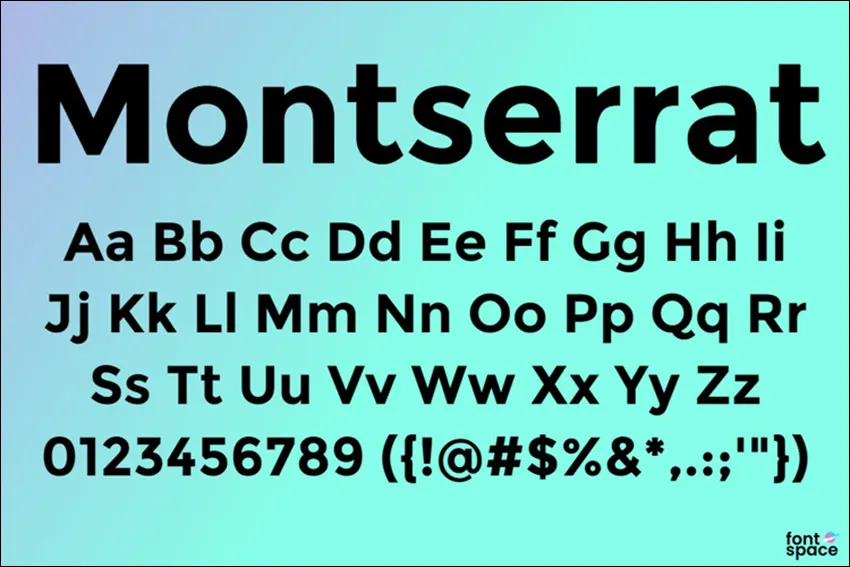
Font pertama adalah Montserrat, font sans-serif modern dengan desain tebal, profesional sekaligus menarik secara visual. Cocok digunakan untuk judul dan sub-judul PPT Anda.
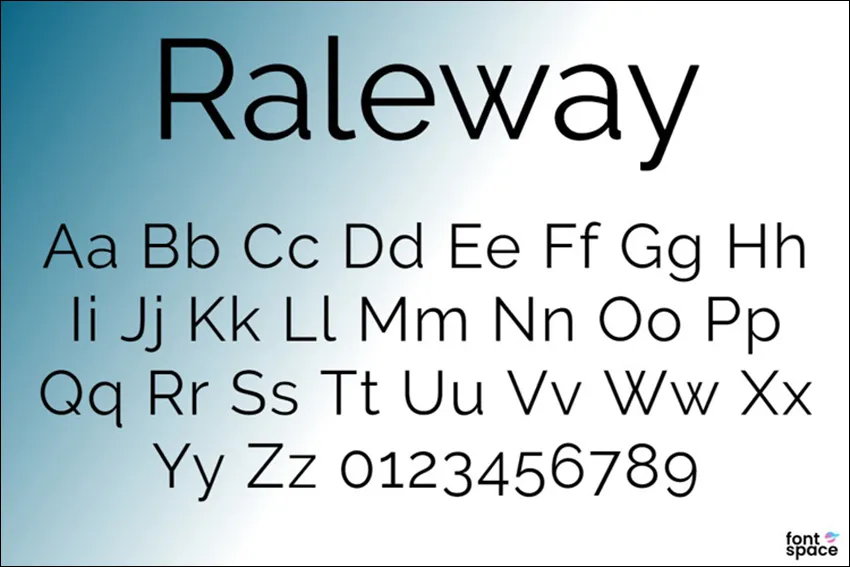
Font kedua adalah Raleway, font sans-serif dengan tampilan yang lebih ringan namun tetap artistik. Cocok digunakan pada hampir seluruh bagian powerpoint, baik judul, sub-judul, maupun body.
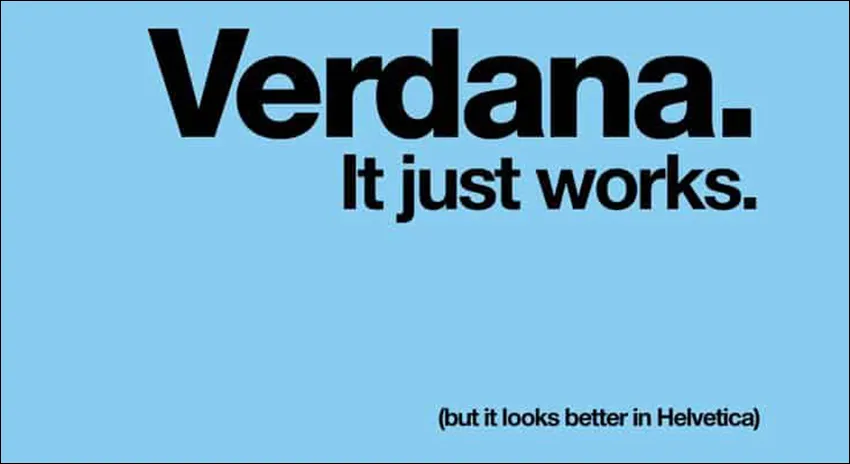
Selanjutnya adalah font Verdana, jenis font sans-serif dengan huruf kecil yang tinggi dan spasi yang lebar, sehingga membuat font ini mudah dibaca meski ukurannya kecil.
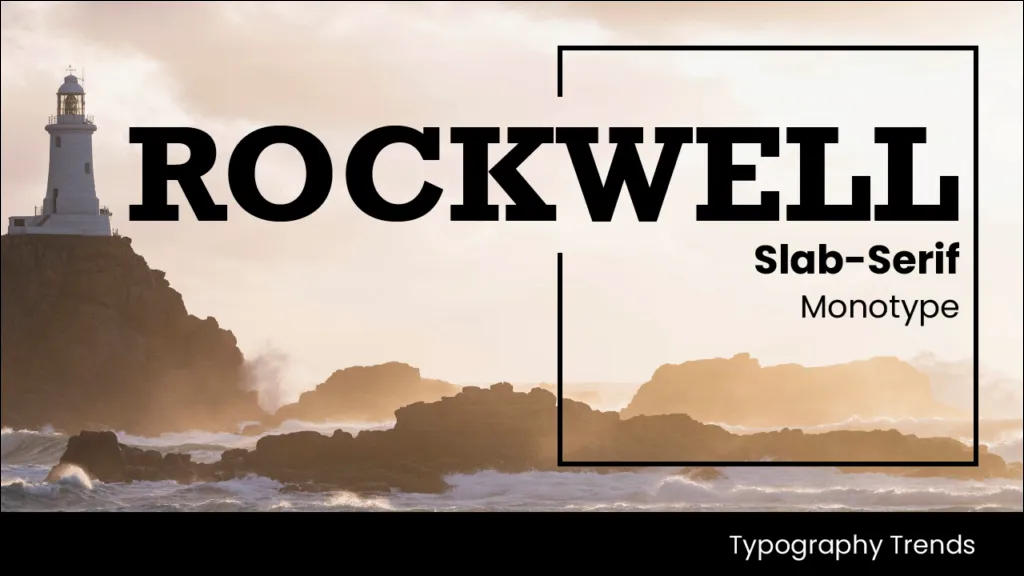
Font ini termasuk font slab-serif dengan desain yang kuat namun tetap hangat, cocok digunakan untuk bagian judul dan sub-judul PPT.
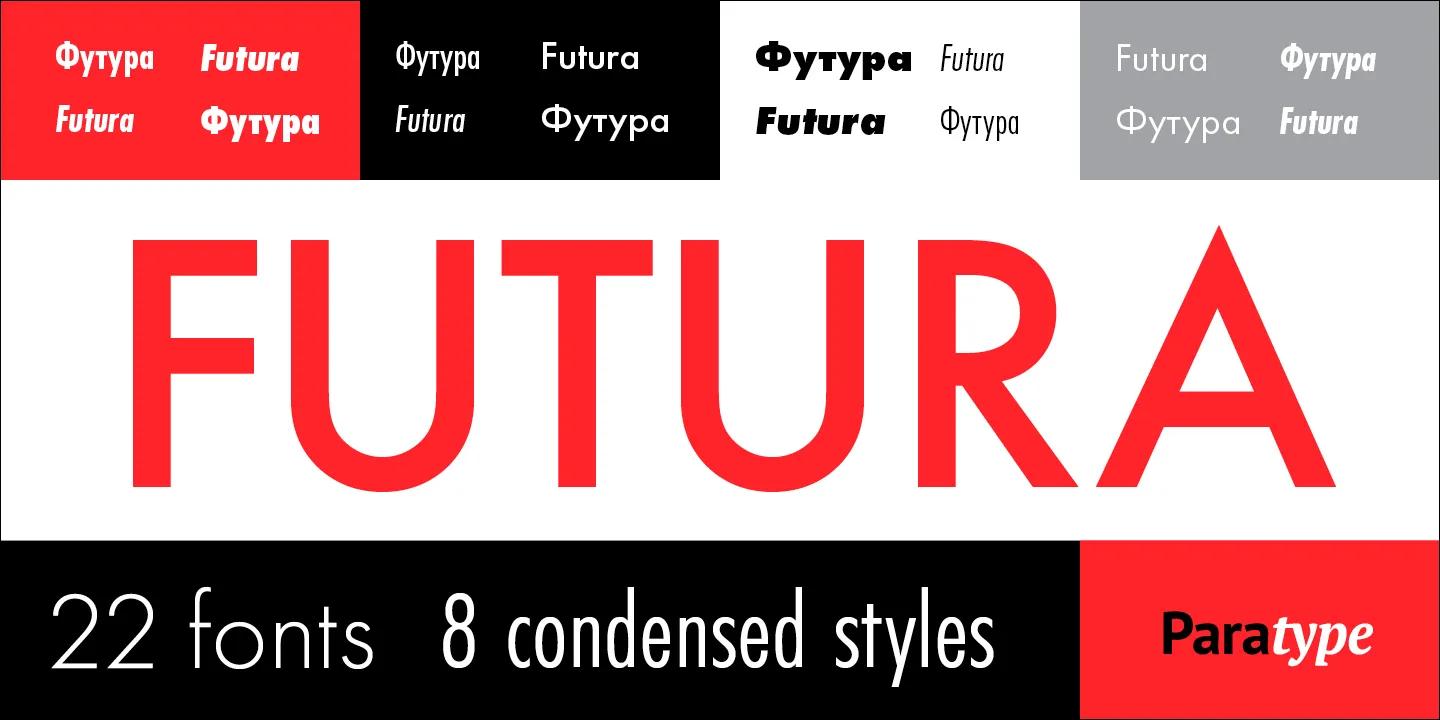
Font slab-serif ini memiliki desain yang bersih dan elegan, cocok digunakan pada seluruh bagian PPT, mulai dari judul hingga konten/body.
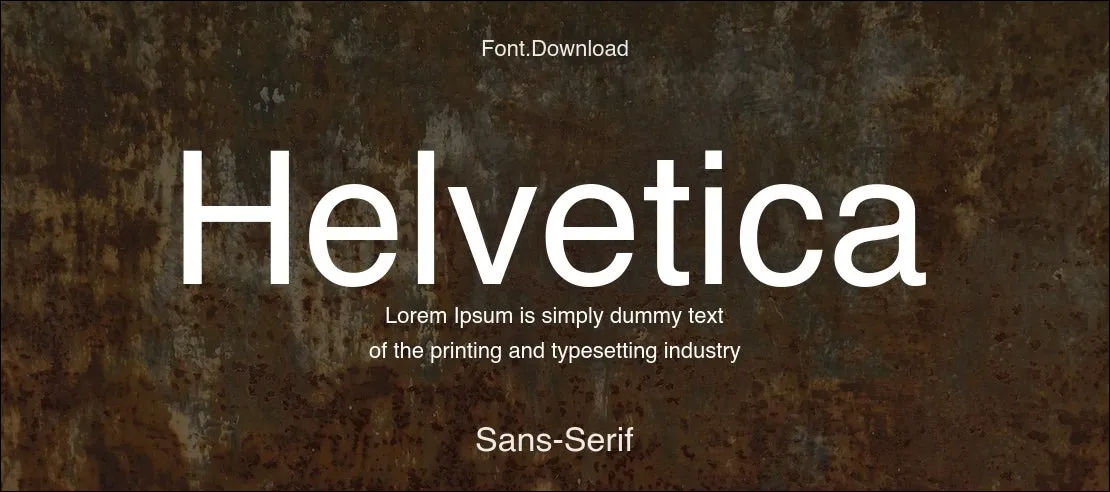
Helvetica merupakan font sans-serif dasar yang paling populer dengan bentuknya yang bagus dalam berbagai gaya, baik tebal maupun kapital semua, membuatnya cocok digunakan pada bagian judul atau sub-judul.
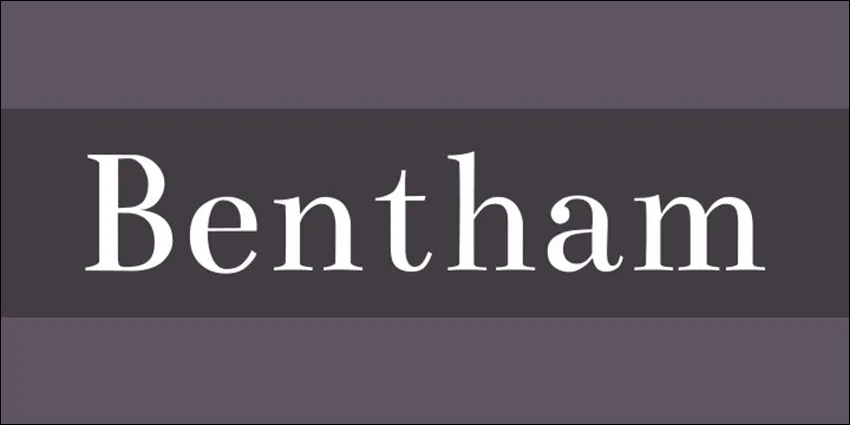
Bentham hadir dengan desainnya yang klasik dan spasi karakternya yang pas, membuatnya cocok digunakan pada bagian judul dan sub-judul PPT.
Font sans-serif ini menampilkan desain huruf yang kokoh dan kuat, membuatnya terlihat menarik jika digunakan pada bagian judul atau sub-judul.
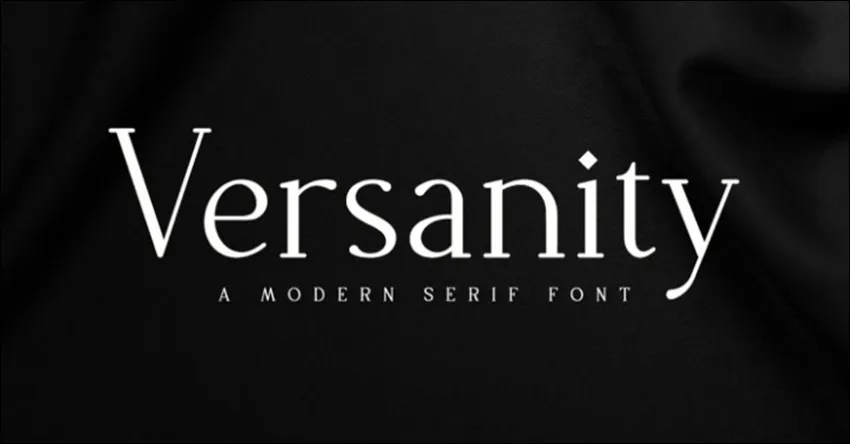
Versanity masuk ke dalam kategori font serif modern dengan desain yang halus dan elegan, cocok digunakan untuk bagian judul maupun sub-judul presentasi Anda.
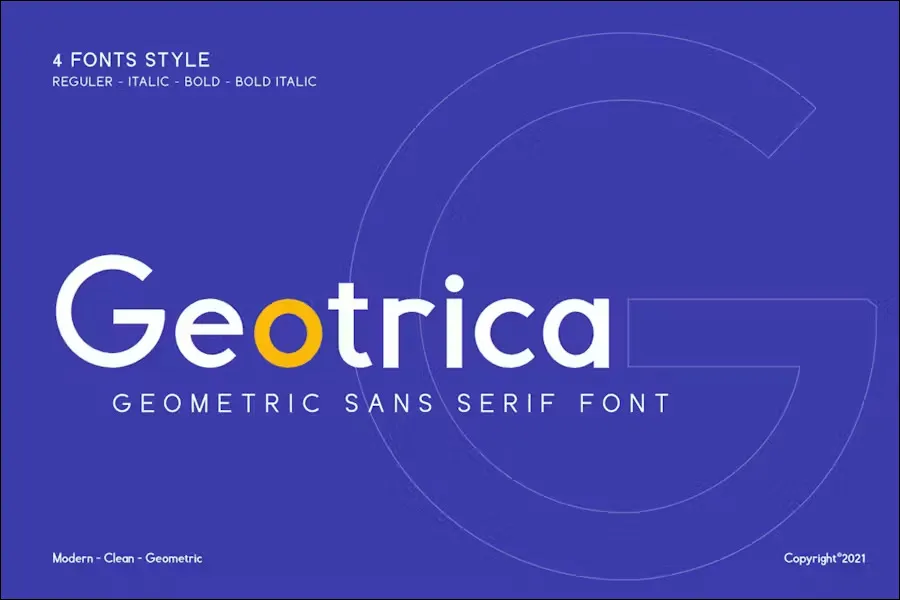
Sebagaimana namanya, font sans-serif ini memiliki bentuk geometris dan desain yang modern. Cocok digunakan untuk header atau sub-header PPT Anda.
Preface adalah font sans-serif dengan tampilan yang segar dan profesional. Cocok digunakan pada semua bagian PPT.
Font ini memiliki desain vintage yang mewah, cocok digunakan untuk bagian judul besar PPT.
Walton merupakan font sans-serif modern yang paling banyak digunakan untuk PPT industri kreatif.
Font serif ini memiliki desain yang halus dan cantik, cocok untuk segala jenis PowerPoint, mulai dari pribadi hingga bisnis dan lain-lain.
Hornimet hadir dengan desain tulisan tangan bold, cocok untuk presentasi dan desain yang kreatif dengan gaya tinta hitam yang autentik.
Molita memiliki desain skip tanda tangan yang elegan dan autentik, cocok digunakan untuk Anda yang ingin menampilkan tanda tangan pada desain dan presentasi.
Font sans-serif ini menampilkan huruf-huruf yang bulat dan sederhana dengan nuansa vintage, cocok digunakan untuk presentasi apa pun.
Wirebet memiliki desain huruf yang bersih dan fungsional, cocok untuk Anda yang ingin membuat presentasi dengan tema desain web.
Font serif ini memiliki desain bold dan modern dengan perpaduan huruf besar dan kecil. Cocok digunakan pada bagian judul atau header PPT.
Daaron hadir dengan 3 gaya, menampilkan huruf-huruf sans-serif yang elegan dan minimalis, cocok digunakan untuk desain dan presentasi apa pun.
Anise merupakan font sans-serif dengan desain yang menawan, menampilkan efek brush tinta yang autentik. Cocok digunakan untuk header PPT.
Dengan garis-garis bersudut dan garis tepi yang membulat, font sans-serif ini sangat cocok digunakan untuk presentasi dengan tema profesional, seperti presentasi bisnis atau perusahaan.
France merupakan font serif yang terinspirasi oleh huruf mesin tik vintage klasik, cocok untuk segala jenis presentasi yang menginginkan gaya retro.
Ukuran font yang pas tergantung pada kebutuhan presentasi dan ukuran layar yang digunakan. Namun, umumnya, ukuran antara 24 hingga 32 untuk body / konten dan 36 hingga 44 untuk judul dapat berfungsi dengan baik.